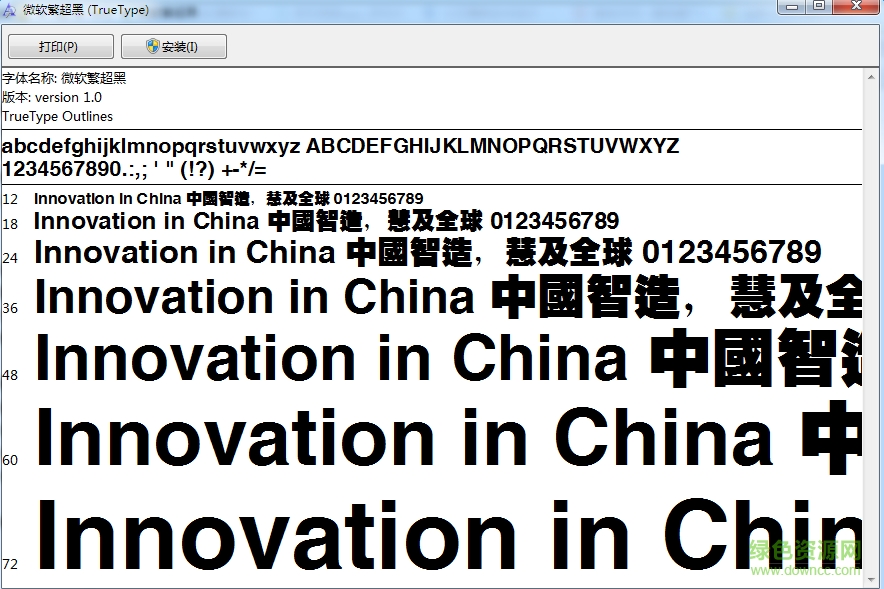
微軟簡(jiǎn)超黑字體是一款粗黑的微軟字體,變化自然,醒目抓睛,可以用在廣告制作、宣傳、卡通圖書或是報(bào)刊的大標(biāo)題等方面,喜歡的朋友快來下載吧!
黑體,機(jī)器印刷術(shù)的歷史產(chǎn)物。至少已有一百年的時(shí)間,黑體漢字抹掉了漢字手書體的一切人為印跡及其造字淵源,沒有手書的起始和收筆;它以幾何學(xué)的方式確立漢字的基本結(jié)構(gòu)(它是構(gòu)建性的,而非書寫性的),其均勻的筆劃寬度和平滑的筆劃弧度表現(xiàn)出一種穩(wěn)定的、充滿機(jī)器意味的無時(shí)間性及共時(shí)性特征。